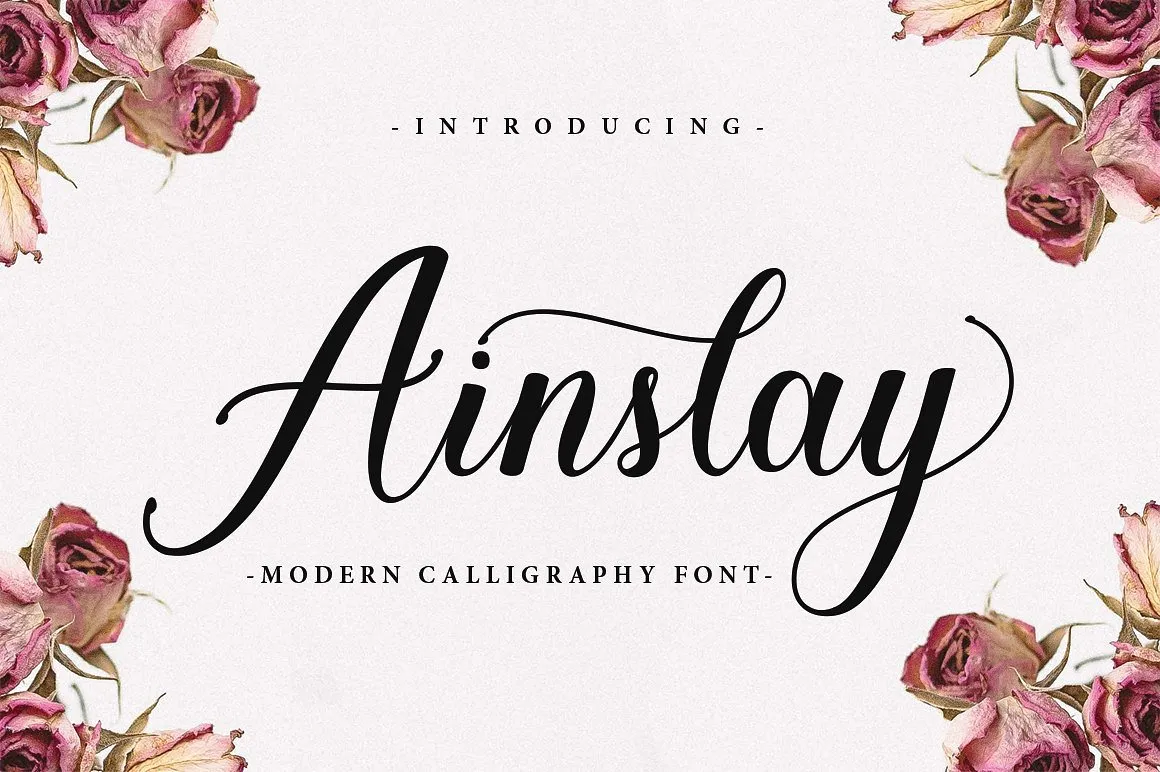
Ainslay Script é uma fonte script moderna com um belíssimo estilo, perfeita para logotipos, cabeçalhos de websites, design de moda e até mesmo cartões de casamento. Seu design elegante inclui letras minúsculas e maiúsculas completas, além de uma ampla gama de pontuação e números, garantindo uma experiência visual fluida em qualquer projeto. Esta fonte vem com três opções de estilo: normal, média e negrito, oferecendo flexibilidade para adaptar à sua necessidade específica. Com suporte multilíngue incluído, Ainslay Script é a escolha perfeita para designers de todos os níveis que desejam um design sofisticado e elegante em seus projetos. Ideal tanto para o dia a dia como para trabalhos de produção especializada, esta fonte é uma excelente opção para adicionar profundidade ao seu trabalho gráfico.